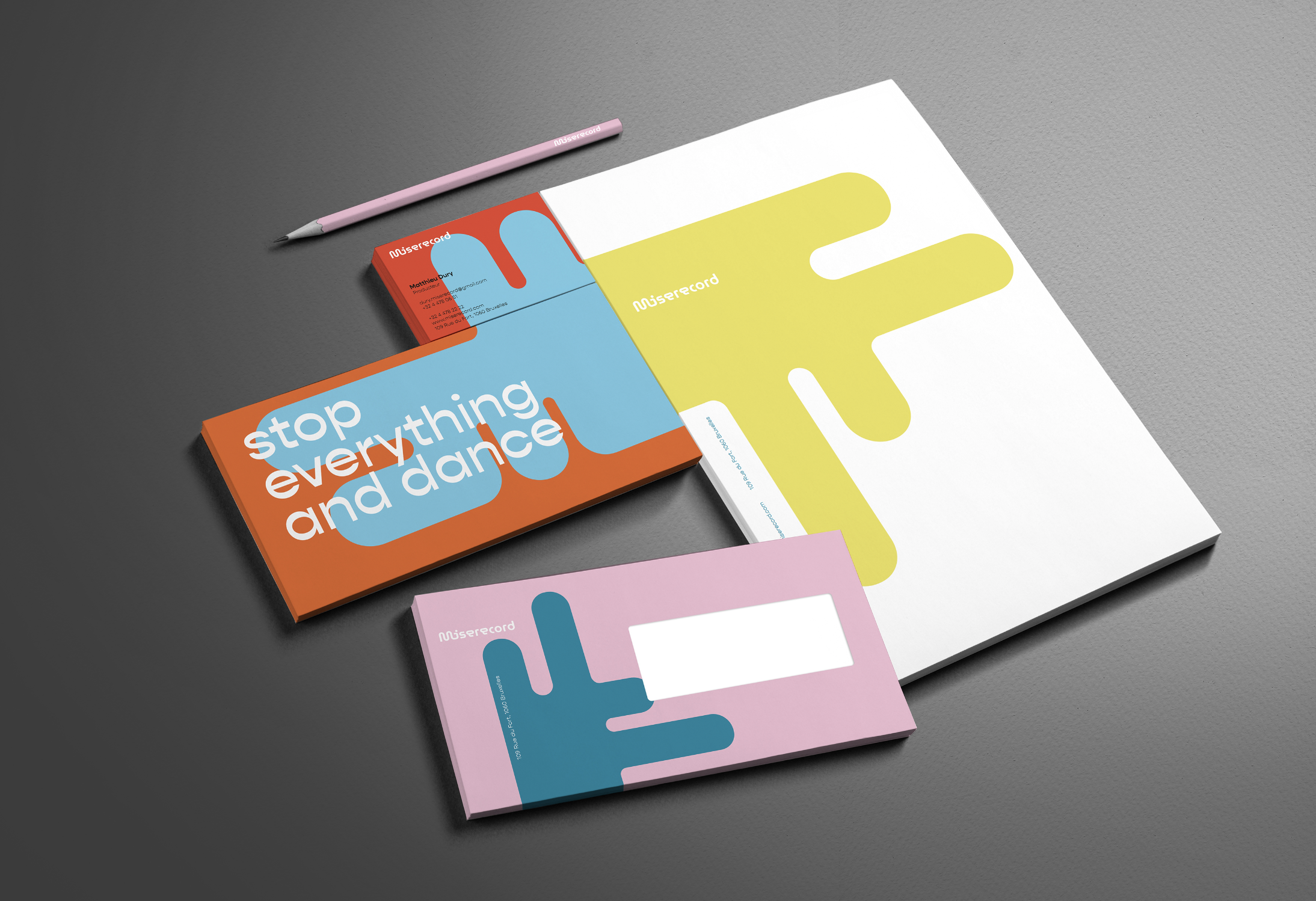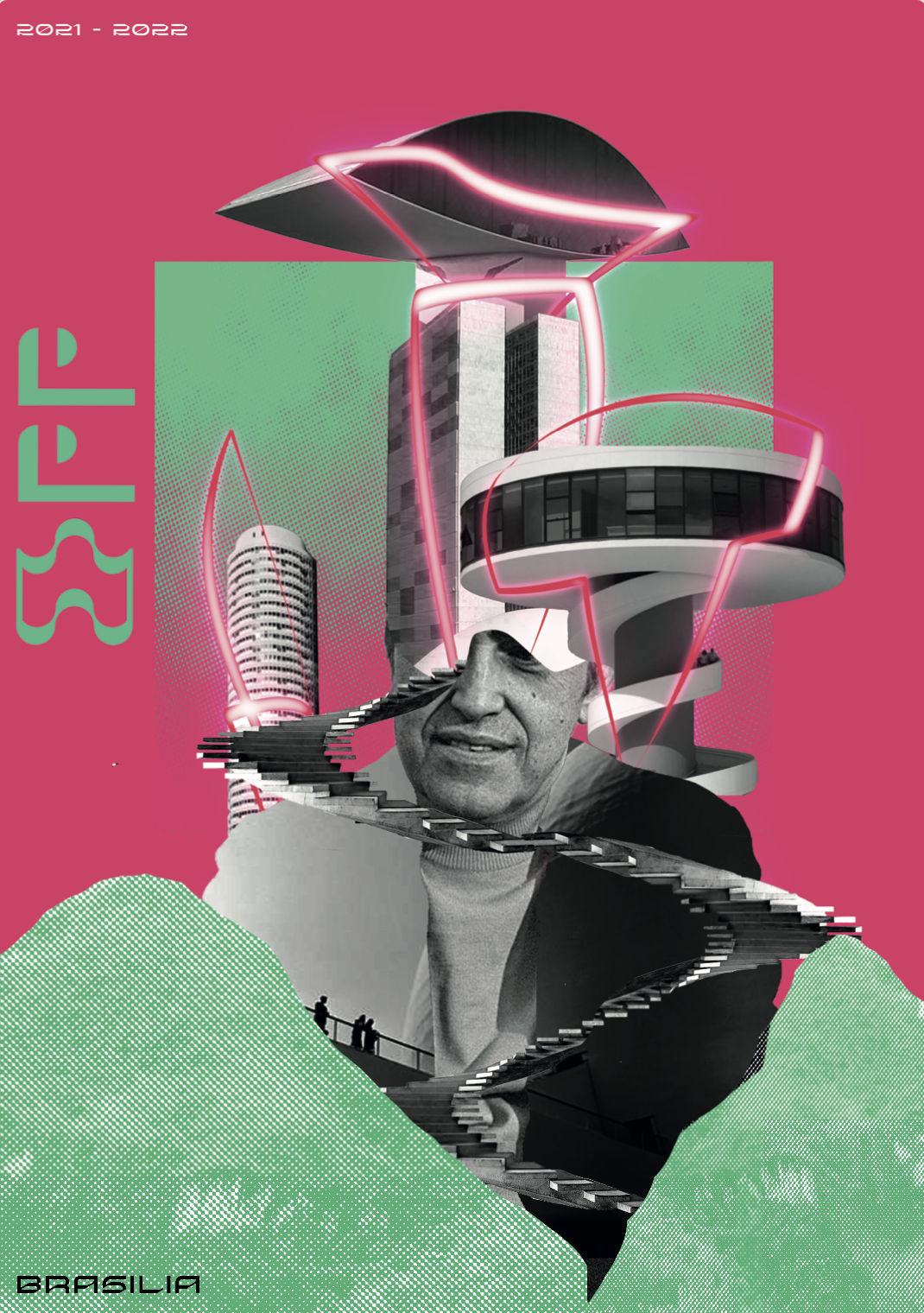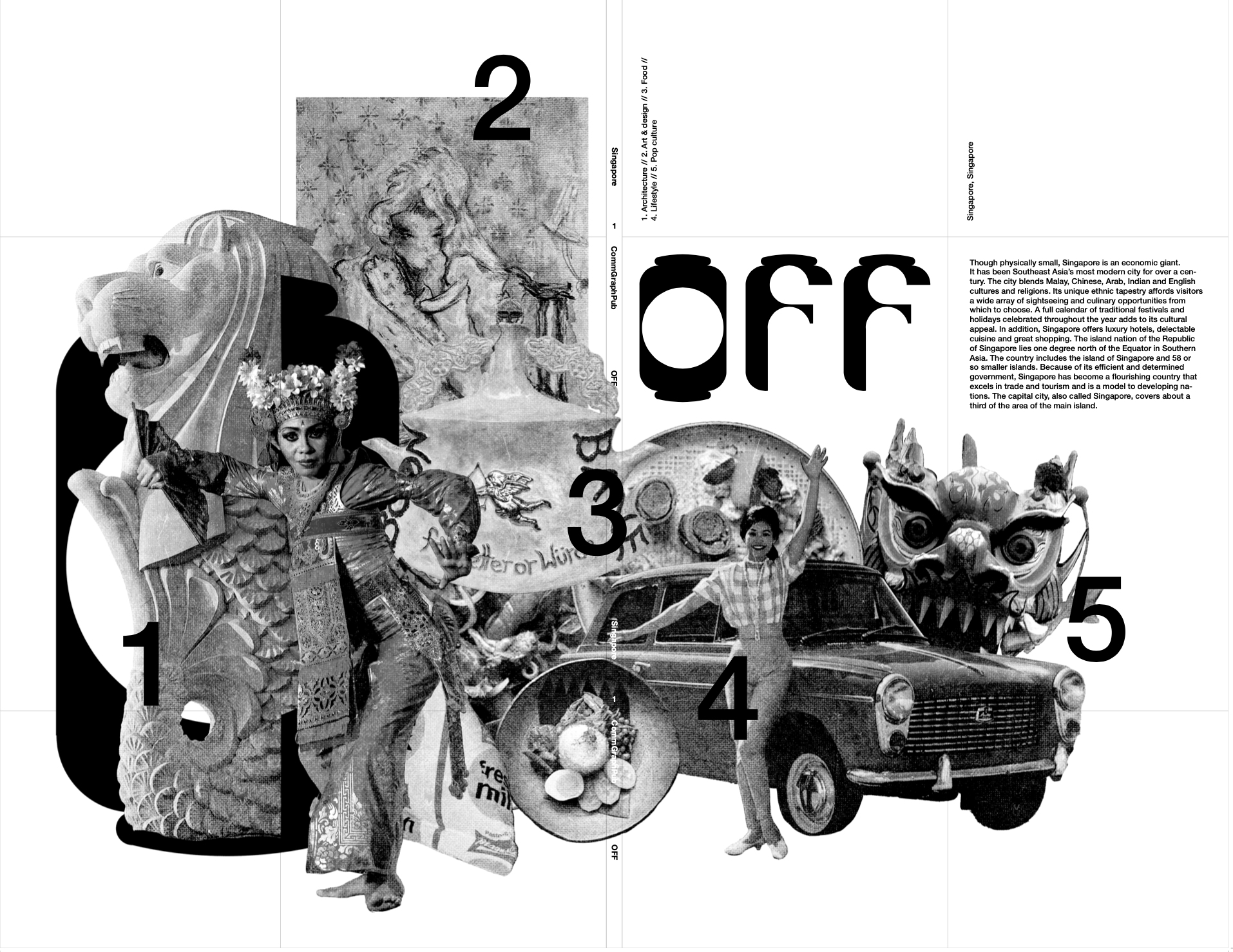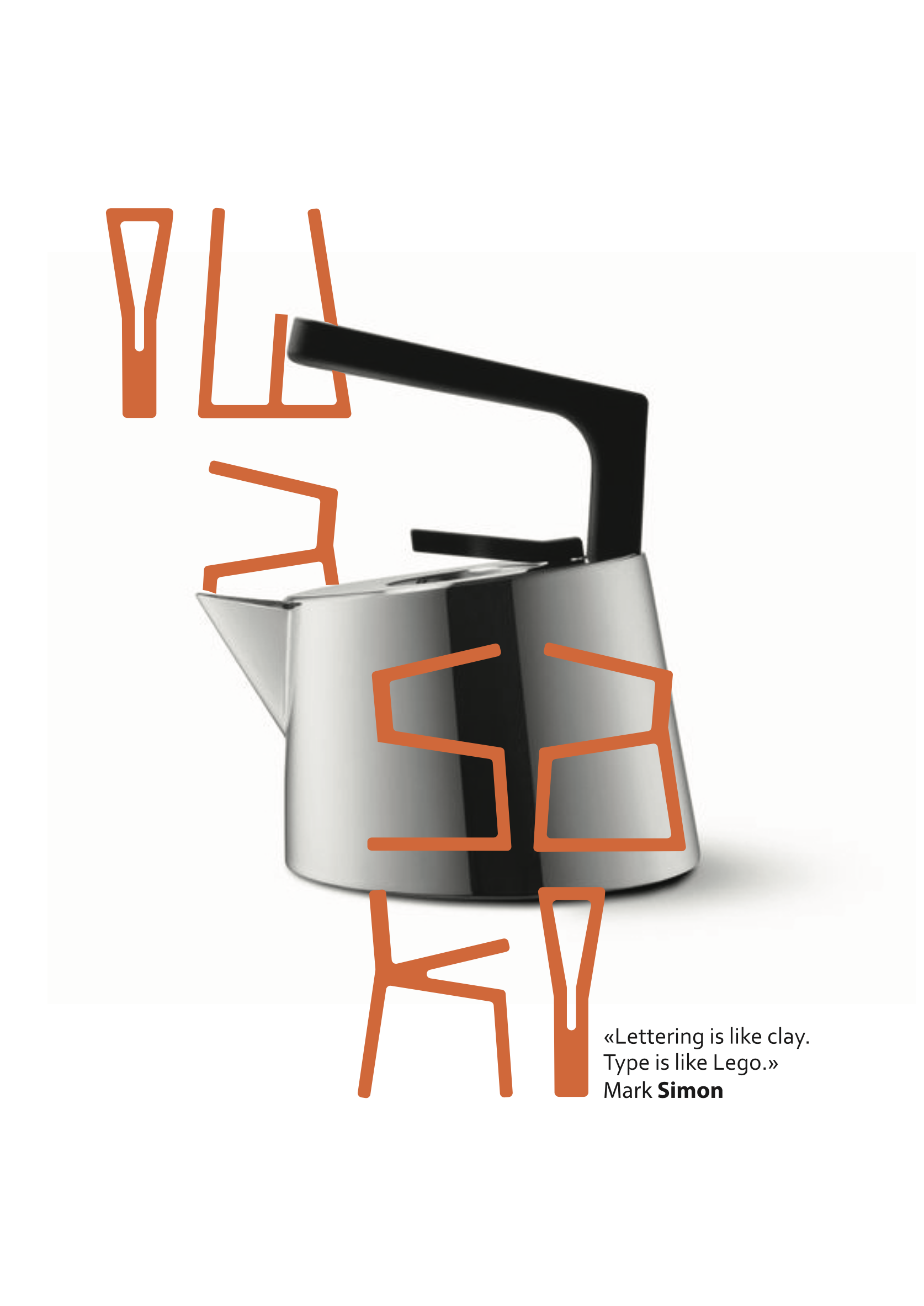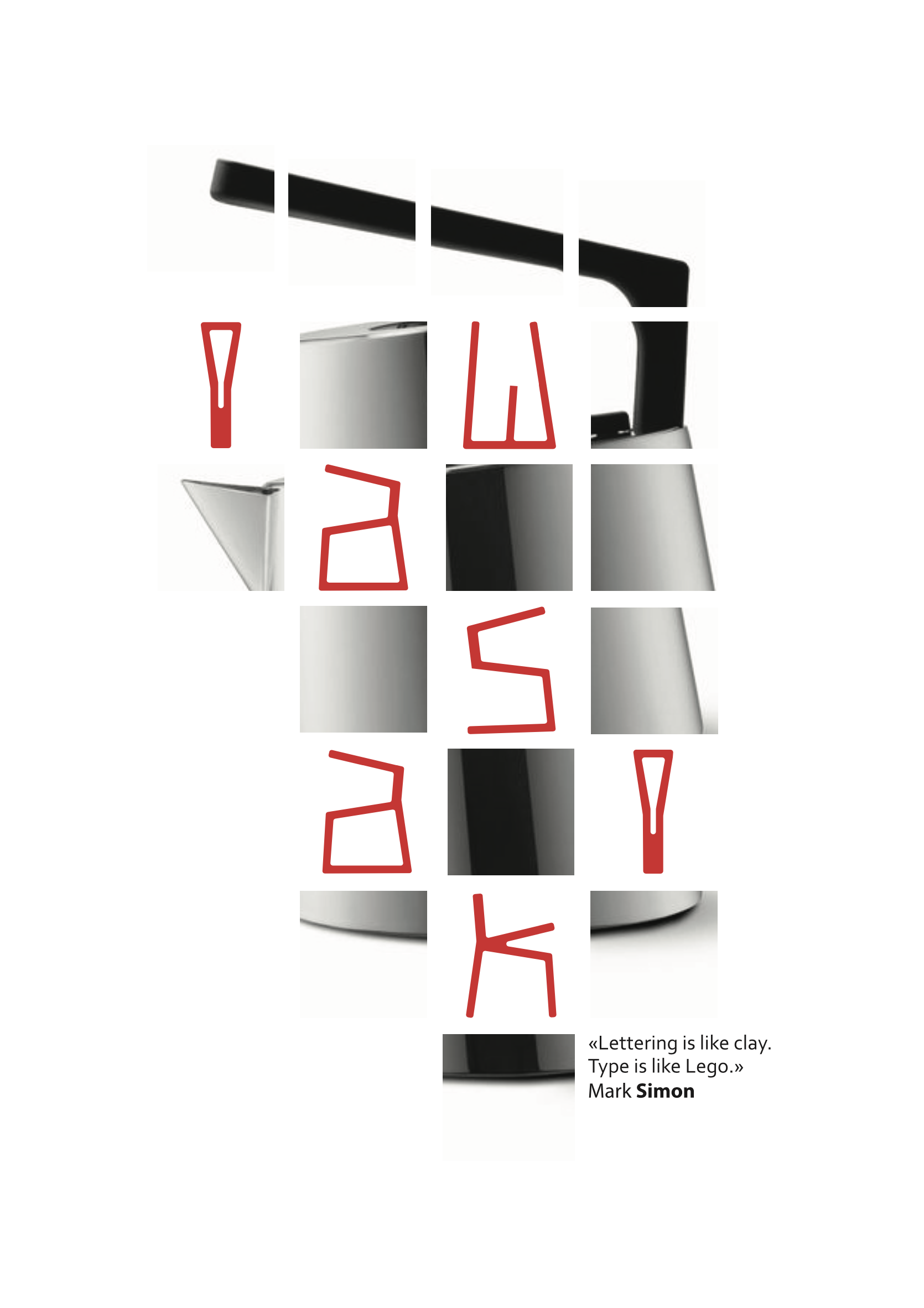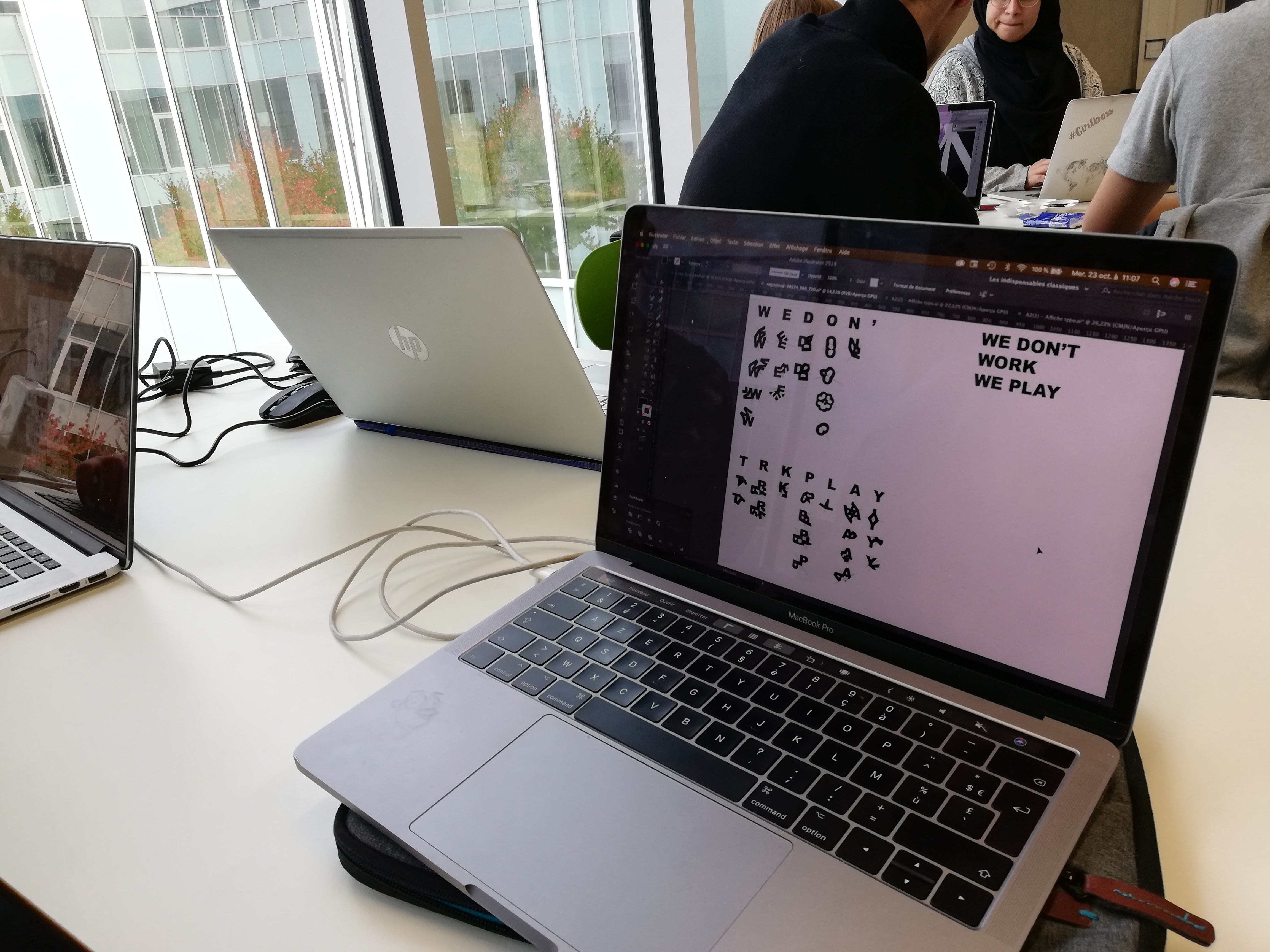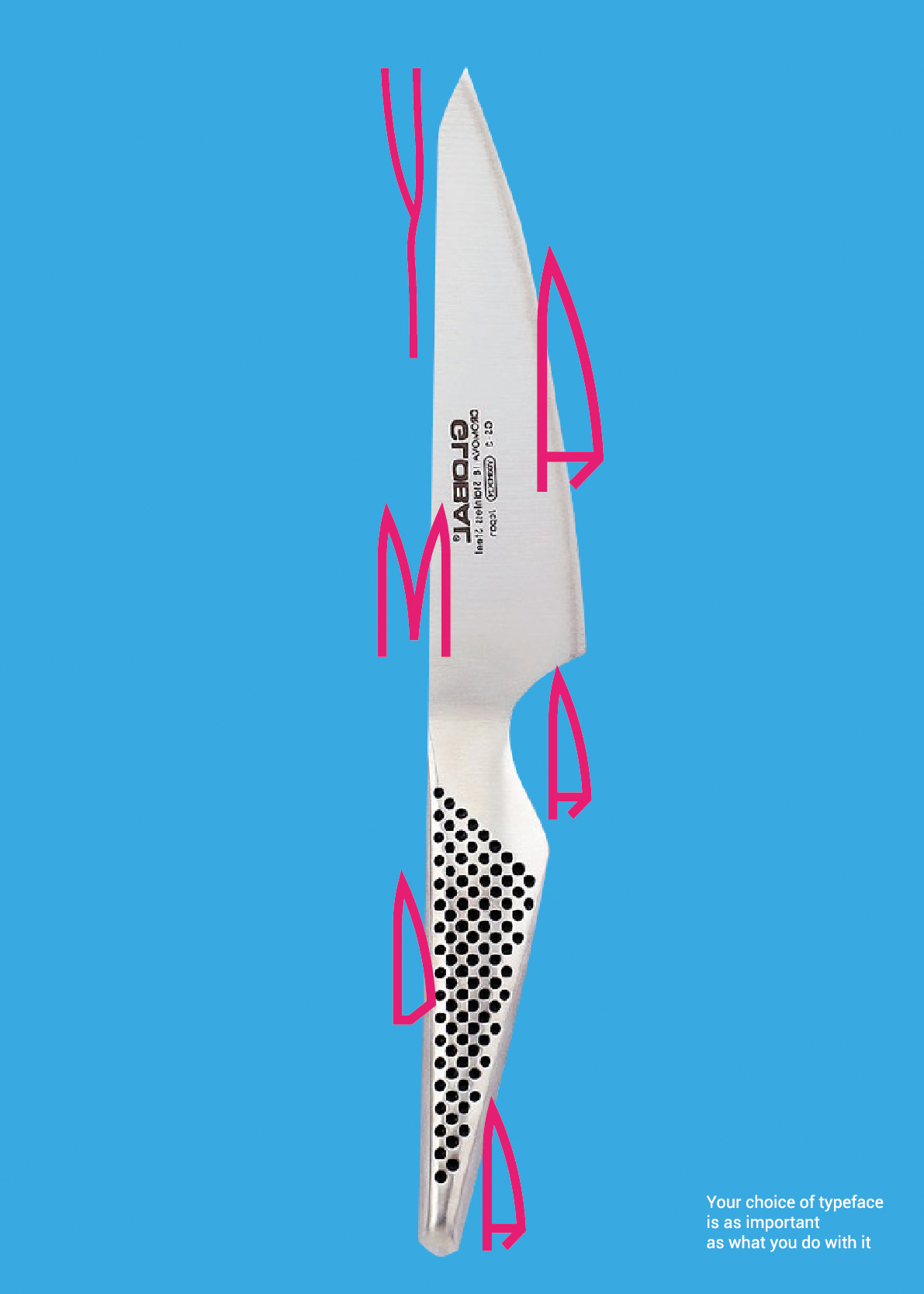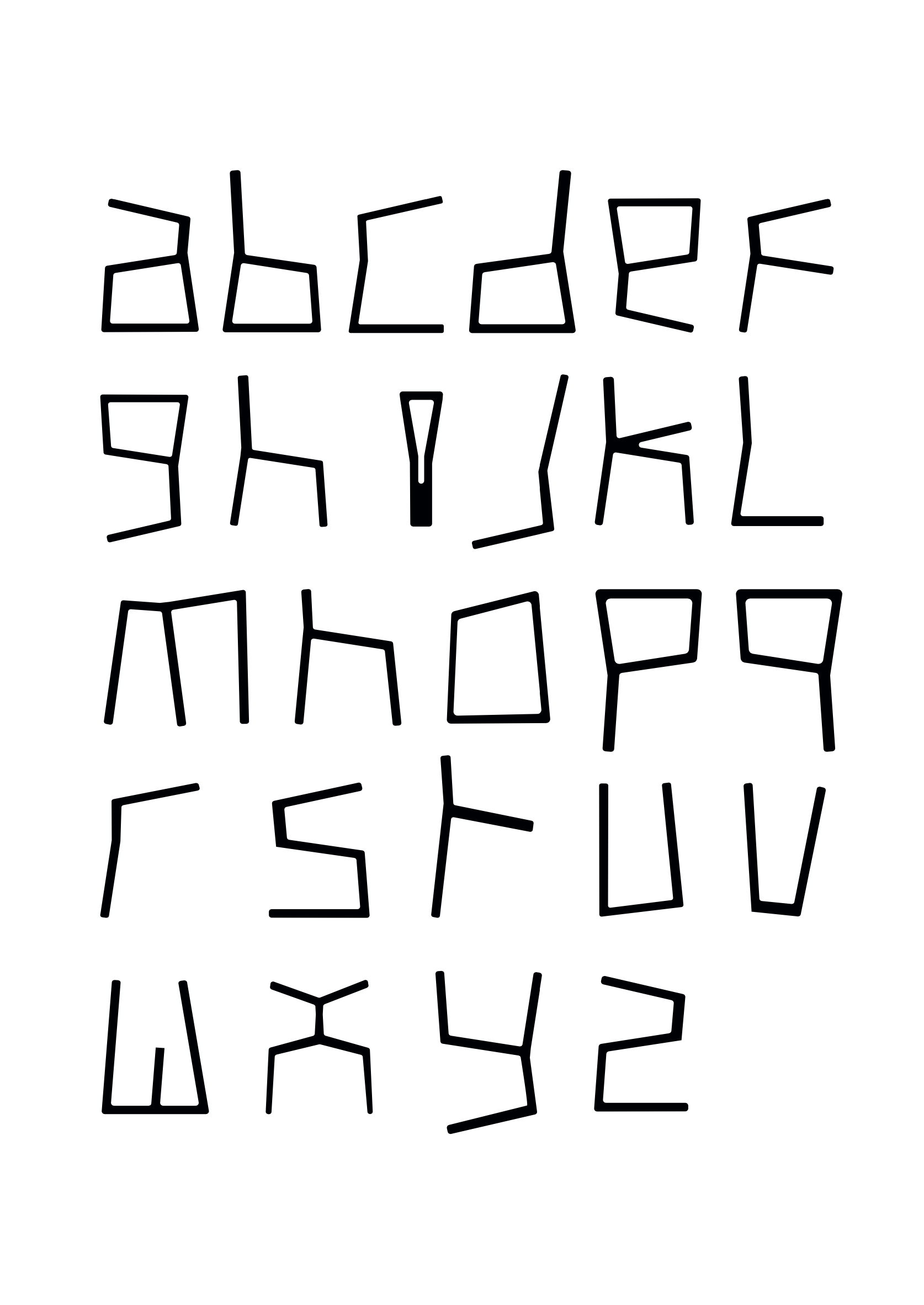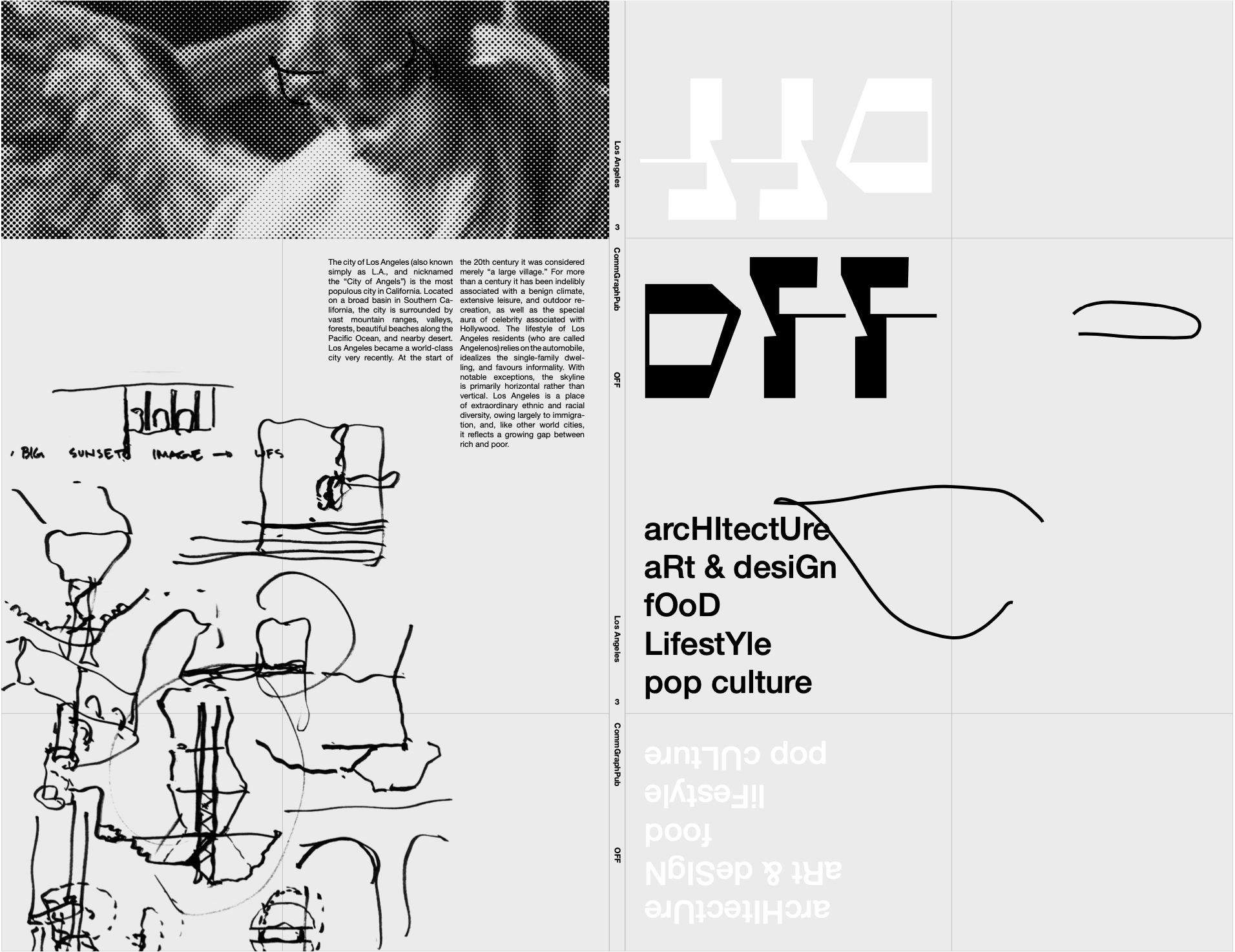
La typographie a le pouvoir d'insuffler une personnalité à un texte, de le combler d'attributs émotionnels. L'aspect « image » de la typo est donc une composante importante. Et oui, les caractères ont un caractère.
La typographie est partout autour de nous: publicités, livres, écrans, panneaux de signalisation, enseignes, logos…
Au-delà du texte, la typographie véhicule une ambiance, un univers… Elle joue avec les codes visuels de nos inconscients collectifs.
En #comgraphpub, nous ne nous contentons pas de choisir des typographies qui se marient bien entre elles. Nous les créons... et ça donne du caractère à nos affiches et nos logos!